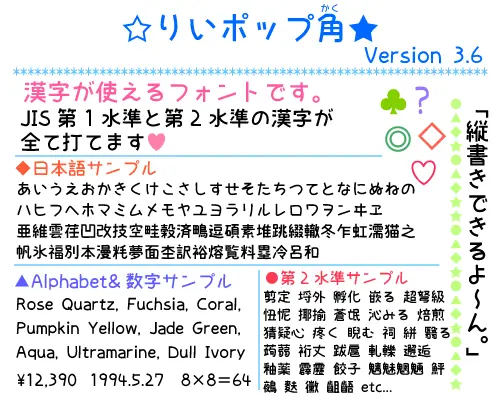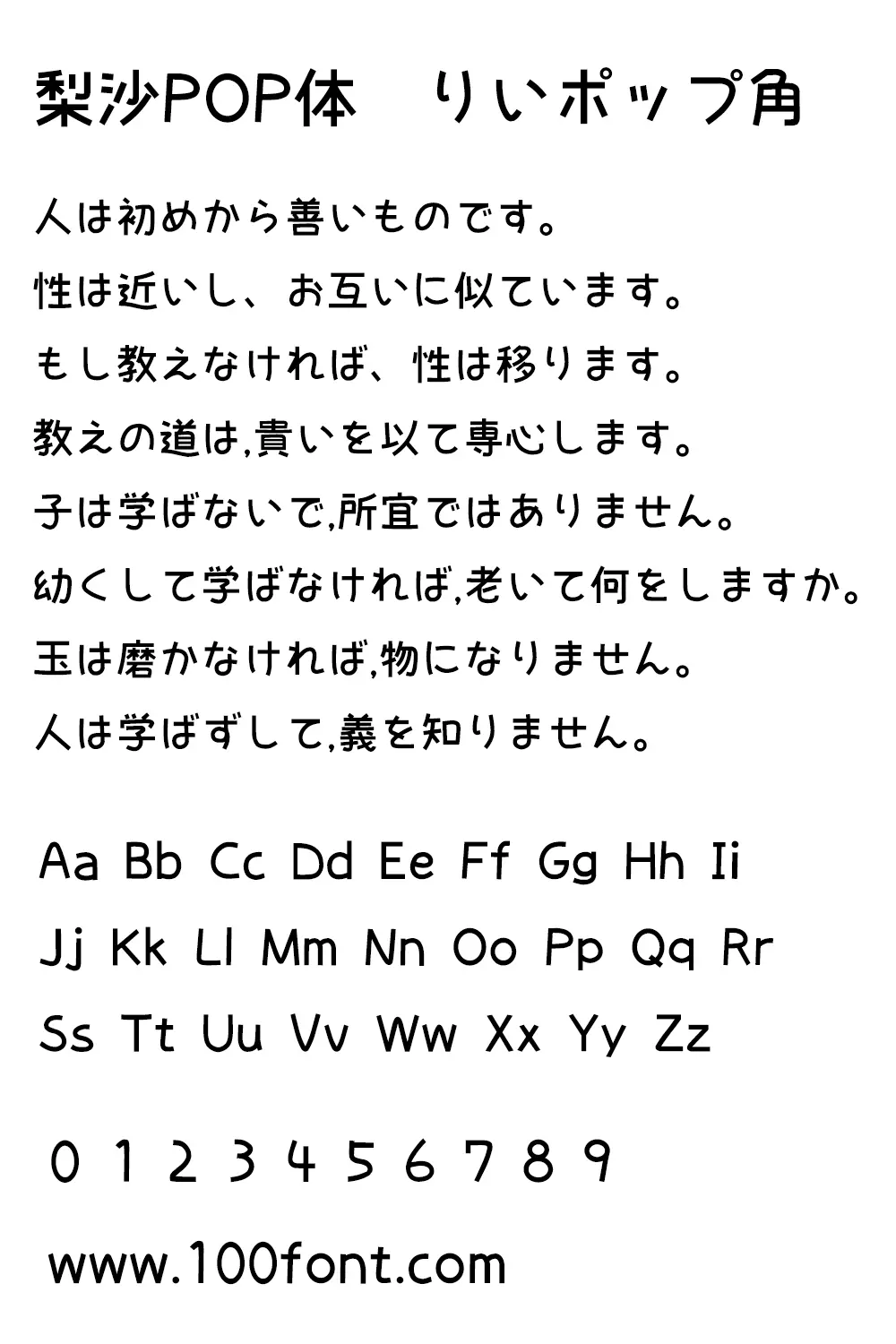
概念(?)是「女孩子的pop體」。雖然不知道是不是這樣做的(笑)。
以容易親近快樂氣氛的字體為目標。字的形狀是以紙上寫的字(方案)為基礎,用Adobe Illustrator製作的。
コンセプト(?)は「女の子っぽいポップ體」です。そのように作れたかはわかりませんが(笑)。親しみやすくて楽しい雰囲気のフォントを目指しました。
字の形は、紙に書いた字(案)をもとに、Adobe Illustratorで作りました。